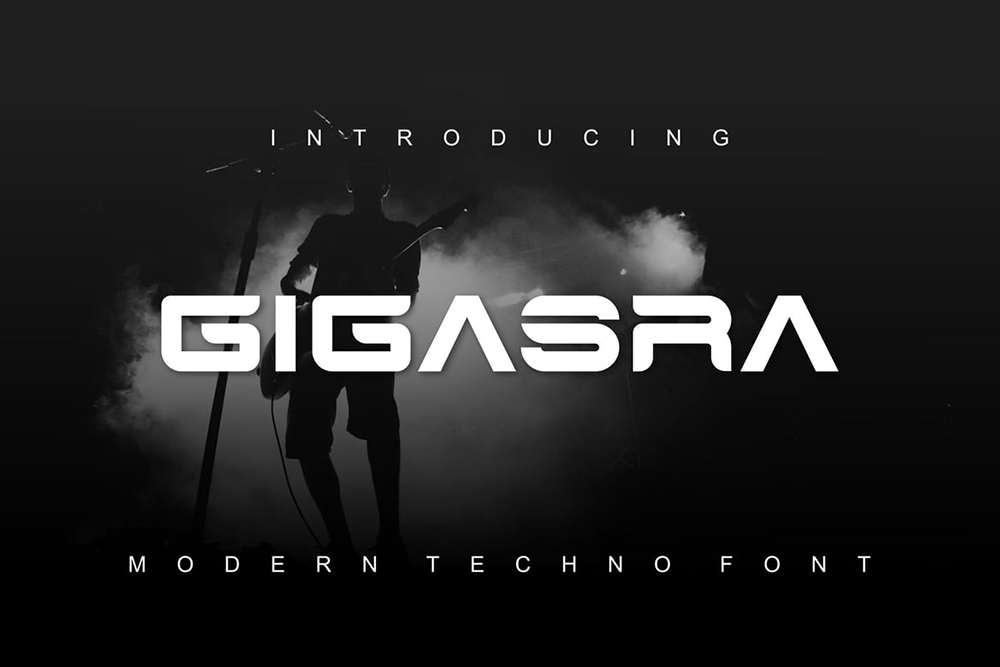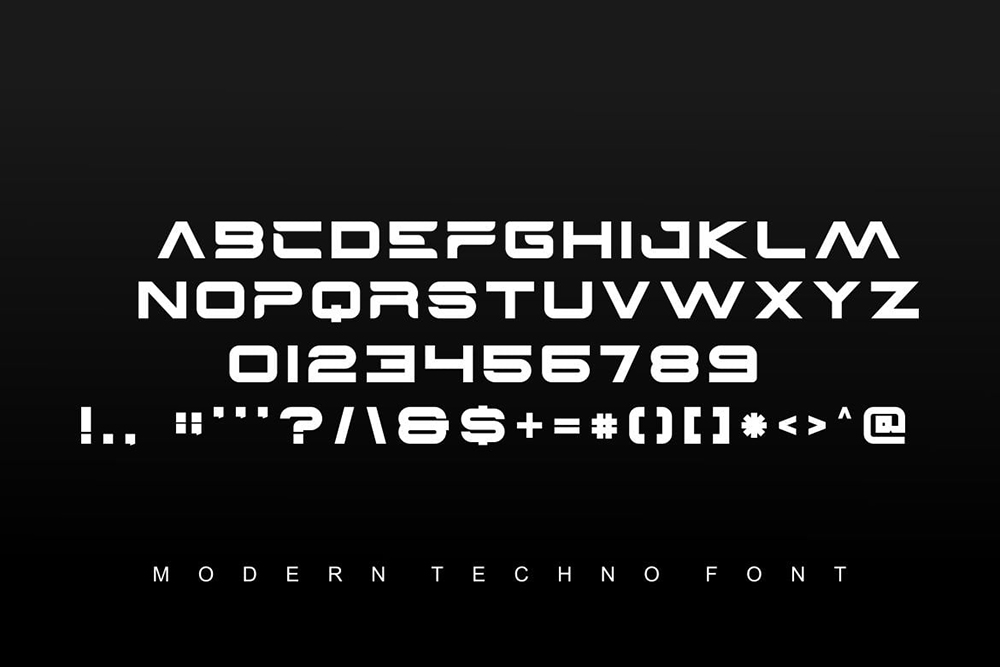
فونت پرمیوم و انگلیسی Gigasra Font یک فونت مدرن، نمایشی جسورانه و اصیل است. این فونت برای هر پروژه برندسازی مانند لوگو، ورزش و بسیاری موارد دیگر مناسب است.
مزایای استفاده از فونت لاتین Gigasra چیست؟